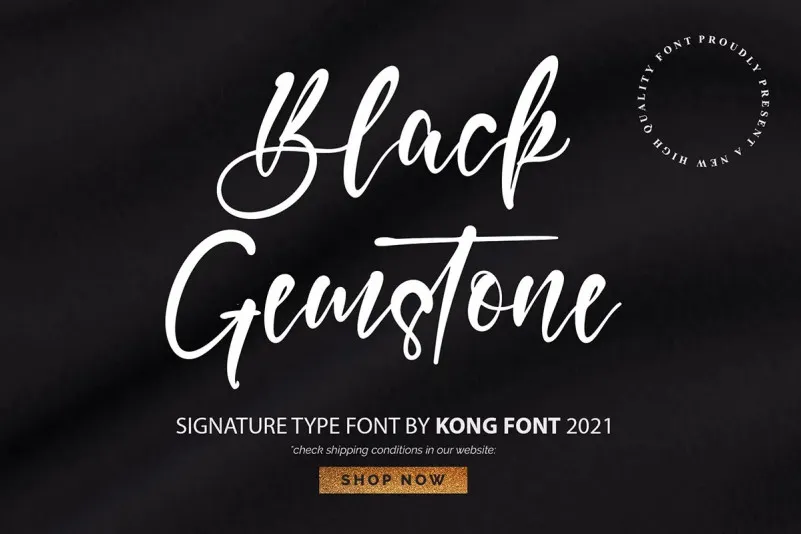
Black Gemstone Font – Download Grátis
A Black Gemstone Font é uma opção perfeita para quem busca personalidade e elegância no design gráfico. Desenvolvida pela Kong Font, essa fonte script moderna está repleta de características que a tornam adequada para diversos usos. Seu estilo elegante faz dela uma escolha ideal para ambientes formais como casamentos ou cartões de convite. Para um toque ainda mais inovador, sua utilização também se destaca em atividades divertidas e criativas, como designs de corte Cricut, silhouettes ou mesmo em títulos de livros e capas, onde a textura única da fonte se destacará ao máximo. Seja para criar um visual acolhedor e sofisticado, ou mesmo para incorporar uma pitada especial em qualquer projeto de design, essa fonte é certamente um must-have. Ideal tanto para o estilo vintage quanto para as tendências mais modernas, a Black Gemstone Font se destaca pela sua elegância inconfundível.